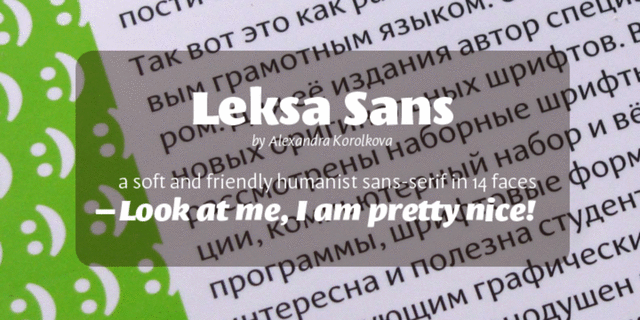
Leksa Sans (Лекса Sans) — это рубленая гарнитура класса гуманистических гротесков с незначительным контрастом в 14 начертаниях в диапазоне насыщенностей от сверхсветлого (Extra Light) до черного (Black). Шрифт проектировался с учетом совместного использования с антиквой Leksa, хотя может с успехом применятся и самостоятельно. Он прекрасно работает в широком диапазоне областей благодаря высокой читаемости в мелких кеглях и оригинальным особенностям формы, проявляющимся в крупнокегельном наборе. Шрифт был спроектирован и выпущен в 2009 году Александрой Корольковой, что нашло отражение в имени гарнитуры. В 2009 году Leksa Sans совместно со шрифтом Leksa была отмечена дипломом жюри международного конкурса «Современная кириллица» в категории супергарнитур. В 2011 шрифт был откорректирован, технически обработан и перестроен в компании ПараТайп.
Ассоциации c семейством Leksa SansКачества и характер:
деликатный, чистый, легкий, прохладный, свежий, модный, доверительный, доступный, комфортный, образованный, современный, культурный, гуманитарный, вежливый, тяжелый, заметный, яркий, активный, броский
— Особенности семейства Leksa SansХит десятилетия: